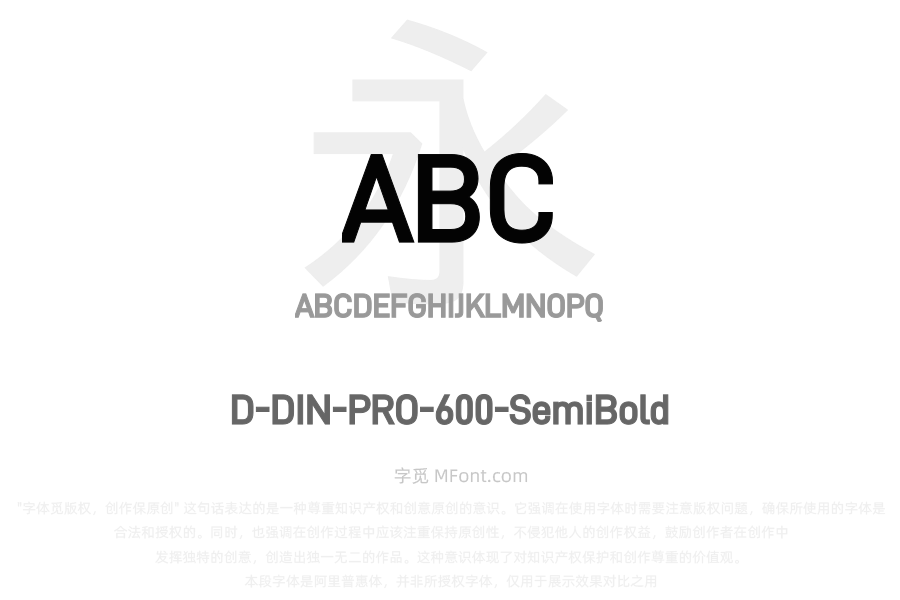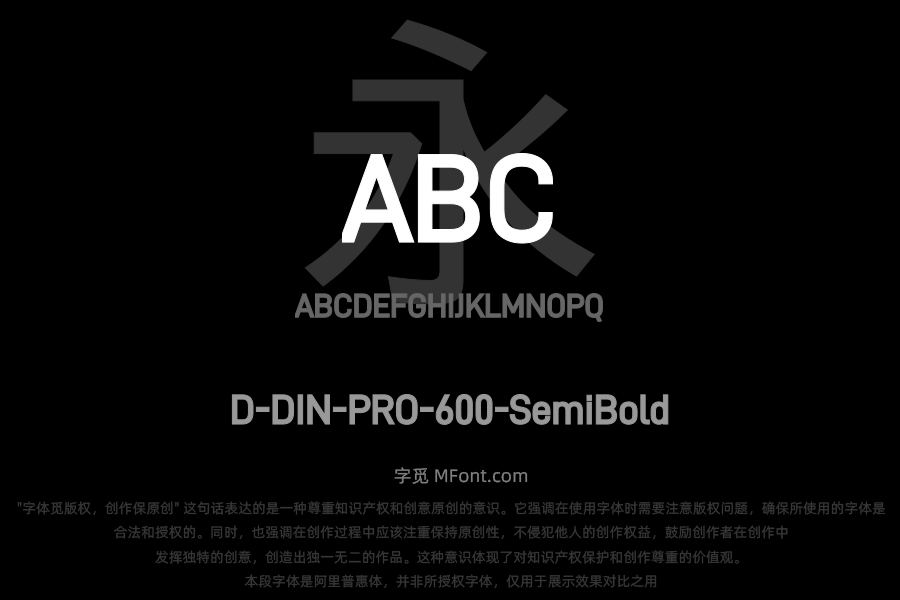
D-DIN-PRO-600-SemiBold
字体全名: D-DIN-PRO-600-SemiBold
铸字厂: D-DIN字体
设计师: Chrles Nix
字体简介: D-DIN-PRO-600-SemiBold,是D-DIN-PRO其中一个regular字重,一共有6个字重可选择,该字是由Adrian Frutiger于1997年设计的无衬线字体。它是DIN字体家族的现代诠释,最初是为1930年代的德国路标设计的。它是一种多用途字体,可用于印刷、网络和移动设备等各种用途。这款经典的类DIN设计现代化的必备字体现在包括从Regular到Heavy的六种字重。D-DIN PRO是一种平衡和易读的字体,既现代又永恒。它是各种项目的不错选择,并且为任何设计增添一丝优雅是安全的。